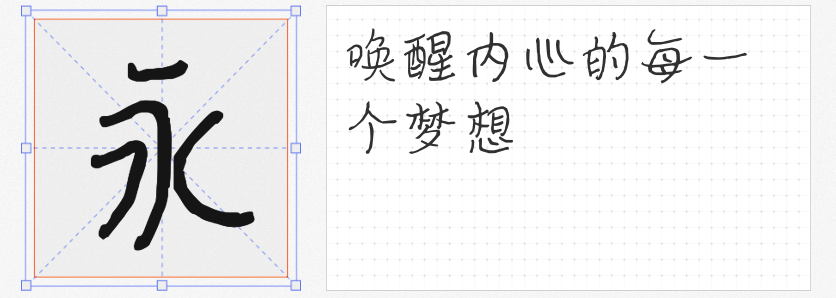
在这个追求个性化与情感共鸣的时代,字体设计不再仅仅是文字的呈现方式,更是一种情感的表达。尤其是一些长得很可爱的手写体,它们以其独特的魅力赢得了无数设计师的喜爱。今天,我们将为大家推荐四款极具代表性的可爱手写字体:字圈也字杰瑞手迹、MyFont濑户风车简、高手兵克笨笨体以及MyFont凌渡猪猪简。让我们一起来探索它们的特点及在设计中的应用吧!
特点:“字圈也字杰瑞手迹”以其圆润可爱的笔画和略带稚气的造型著称。每一个字符都像是一个小精灵,跳跃在纸上,散发着无尽的活力与欢乐。这款字体的设计灵感来源于儿童绘画,因此它充满了童真与想象,让人一眼就能感受到那份纯净的美好。
设计用途:这款字体非常适合用于儿童书籍、动画片头、玩具包装、教育产品等设计领域。它能够迅速拉近与儿童之间的距离,激发孩子们的好奇心与创造力。同时,对于成人来说,使用“字圈也字杰瑞手迹”也能唤起内心的童真,为生活增添一份乐趣。
特点:“MyFont濑户风车简”是一款融合了日式风情与现代简约风格的可爱手写字体。其笔画流畅而优雅,字形简洁而不失趣味性,宛如一阵清新的海风拂过面庞。这款字体不仅保留了手写体的自然感,还加入了一些细腻的设计细节,使其更加生动有趣。
设计用途:这款字体适用于各种生活方式类的设计项目,如美食博客、旅行日记、手账应用等。它能够为内容增添一份温馨与浪漫,让读者在阅读时仿佛置身于一个充满阳光与微风的美好世界。
特点:“高手兵克笨笨体”是一款非常独特且富有幽默感的手写字体。它的笔画粗细不一,字形略显笨拙,但却因此而显得格外可爱。每一个字符都像是一位憨态可掬的朋友,让人忍不住想要亲近。这款字体的设计灵感来源于日常生活中的点滴趣事,因此它充满了生活的气息与温度。
设计用途:这款字体特别适合用于幽默漫画、搞笑视频、社交网络配文等场合。它能够有效提升内容的娱乐性和亲和力,使观众在轻松愉快的氛围中享受阅读的乐趣。
特点:“MyFont凌渡猪猪简”是一款以卡通猪为主题设计的手写字体。它的笔画圆润饱满,字形简洁明快,每个字符都仿佛是一个活泼可爱的小猪。这款字体的设计灵感来源于动物世界的美好,旨在通过可爱的形象传递正能量。
设计用途:这款字体非常适合用于儿童用品、宠物相关产品、节日贺卡等设计项目。它能够为作品增添一份童趣与温馨,使目标受众在使用过程中感到快乐与满足。
总之,可爱手写字体以其独特的魅力和广泛的应用场景,成为了许多设计师不可或缺的创意工具。无论是想要为作品注入一丝童趣,还是希望传达出轻松愉悦的情感,这四款字体都能为您提供无限可能。希望本文的介绍能够帮助您更好地了解和运用这些萌动心弦的手写字体,创造出更多令人喜爱的设计作品。